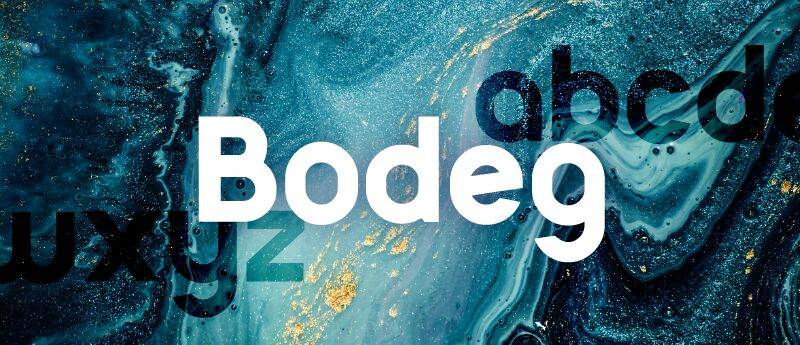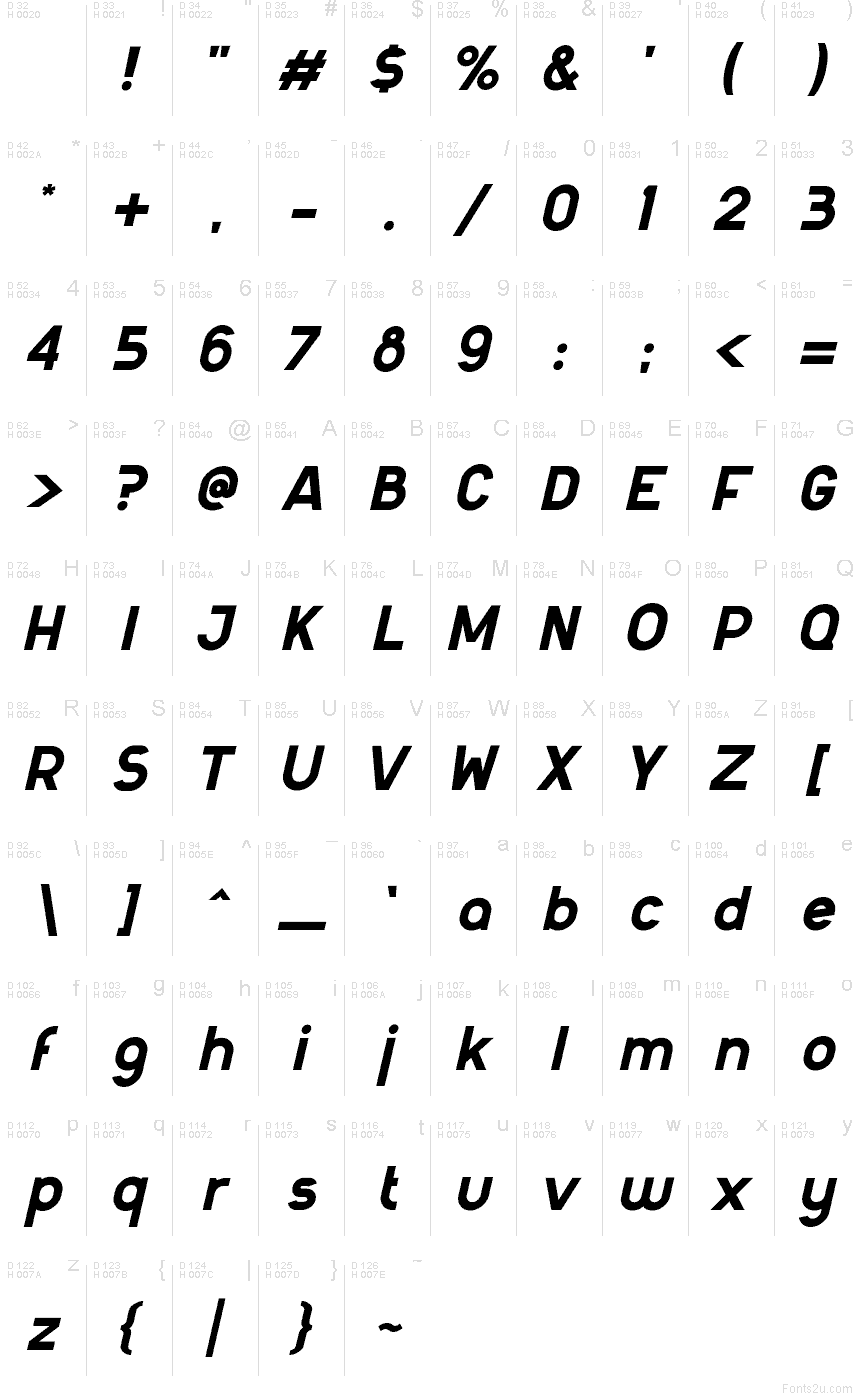
Bodeg
Bodeg, diseñada por Nermin Kahrimanovic, es una tipografía sans serif gratuita e inclinada, con un ritmo rotundo y redondeado que evoca la suavidad de los años 70. Las letras se sienten amplias y dinámicas en lugar de rígidas, con curvas generosas, uniones compactas y una inclinación hacia adelante que otorga incluso a las palabras cortas una cadencia fluida y envolvente.
Es ideal para titulares de carteles, portadas de música, branding de cafeterías, portadas de revistas y packaging donde busques algo directo pero amable. Como fuente gratuita, Bodeg también funciona de maravilla en gráficos para redes sociales y títulos breves; sus formas gruesas y vivaces mantienen un tono desenfadado, mientras que su inclinación impulsa el texto con fuerza.